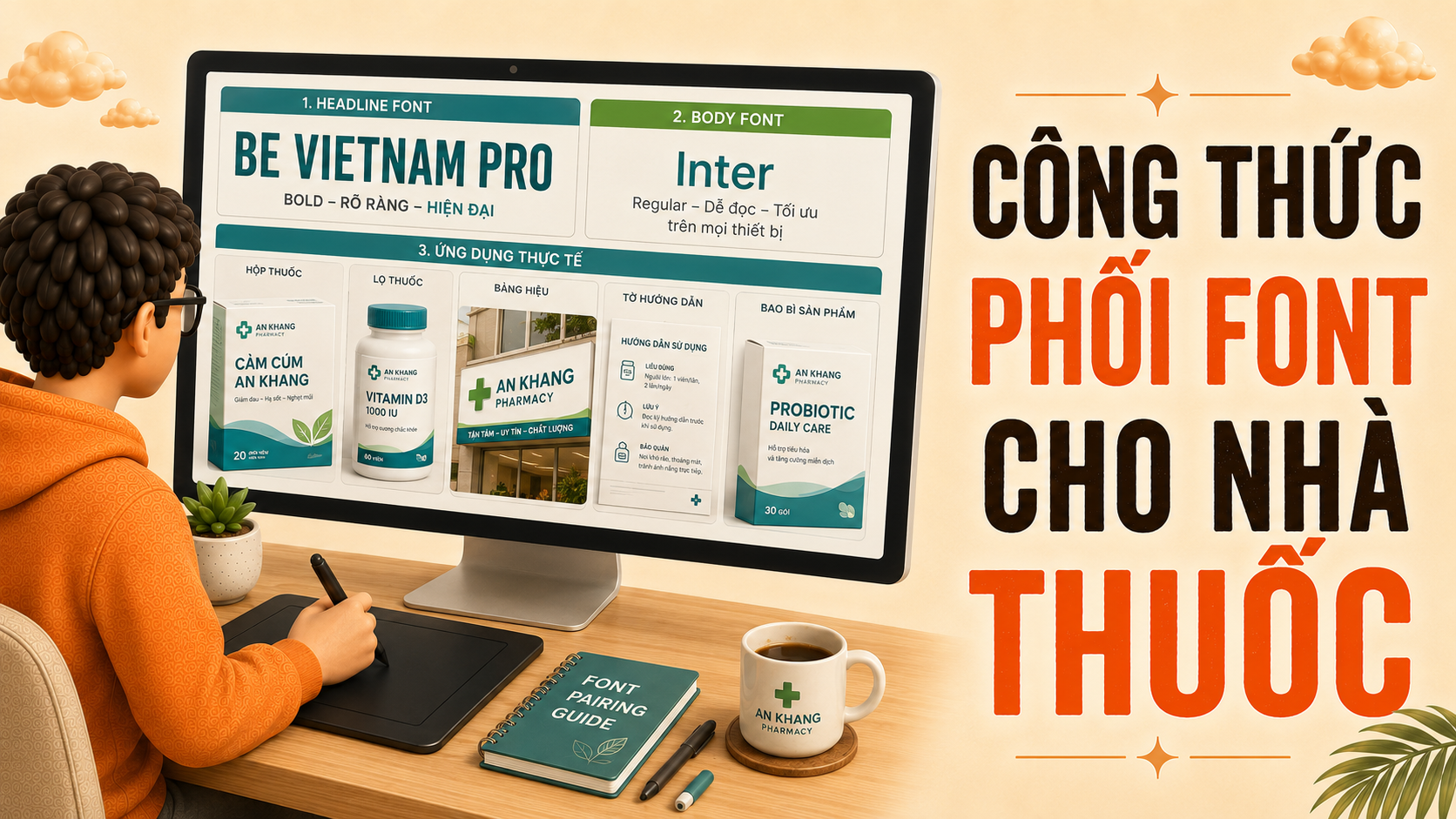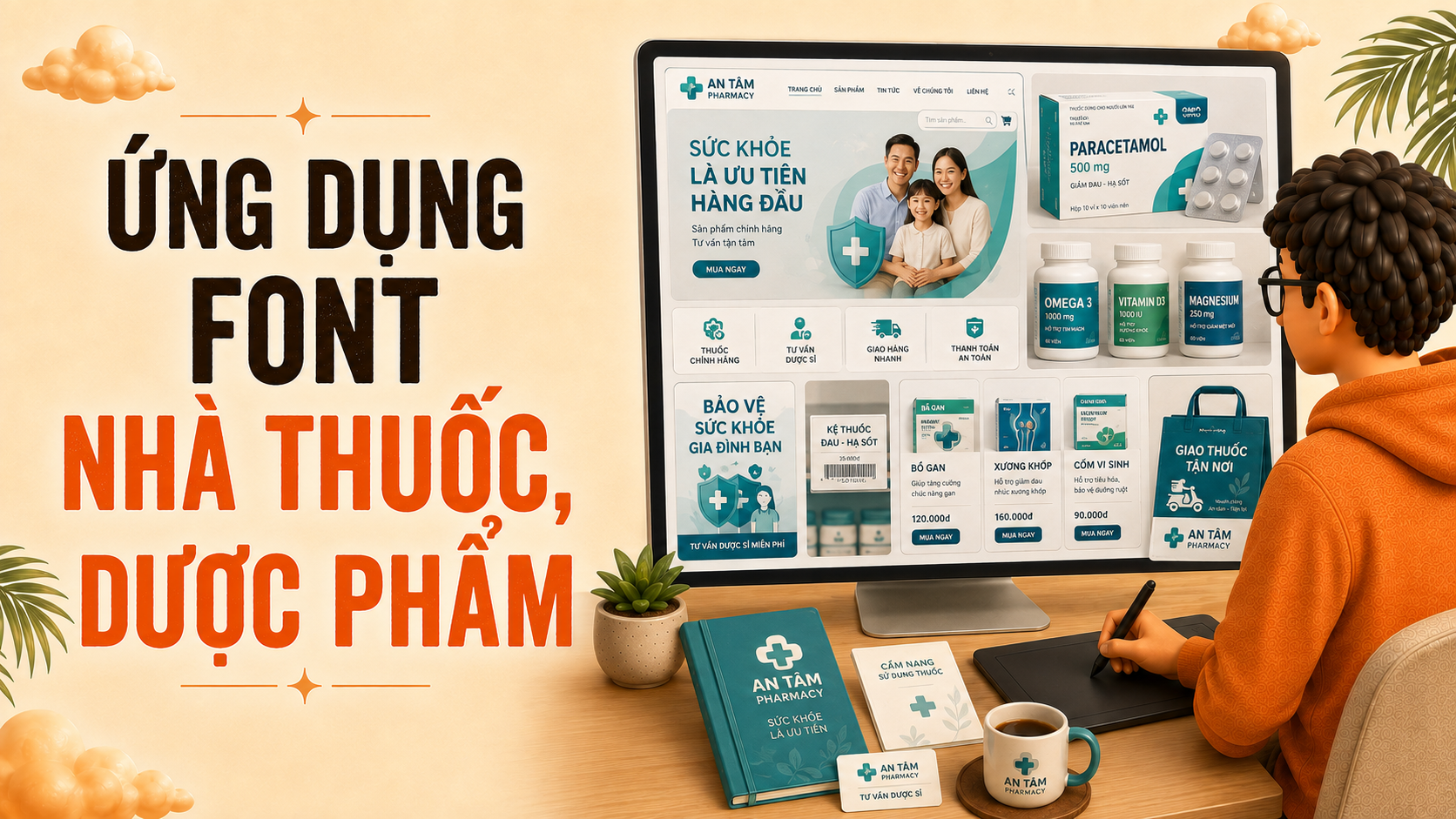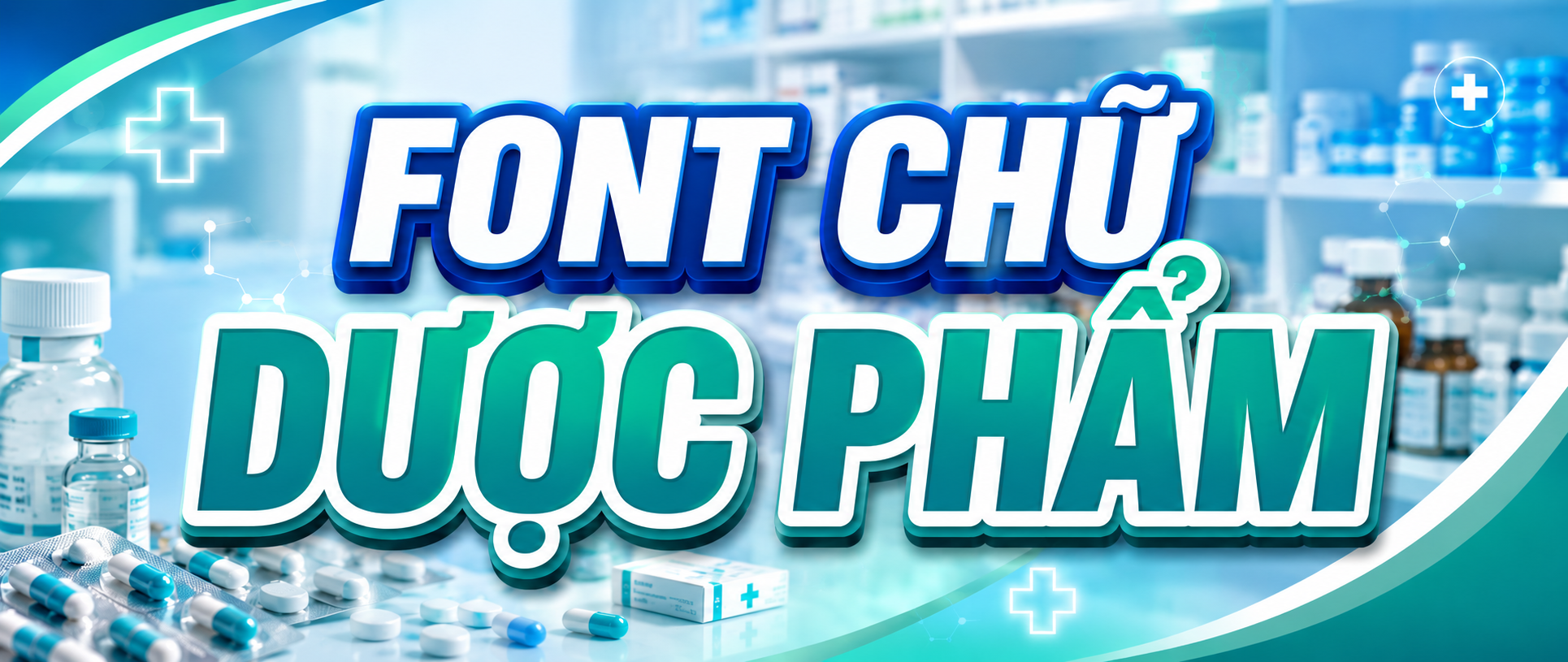
Font chữ nhà thuốc, dược phẩm không thể chọn theo cảm tính như một bài quảng cáo thông thường. Ngành dược cần sự rõ ràng, tin cậy và đúng mực vì người đọc thường đang tìm thông tin liên quan đến sức khỏe, sản phẩm chăm sóc cơ thể, thuốc, vitamin, thực phẩm chức năng hoặc hướng dẫn sử dụng. Một font đẹp nhưng khó đọc có thể làm bảng hiệu kém chuyên nghiệp, bao bì thiếu an tâm hoặc poster tư vấn bị rối.
Nhà thuốc là nơi khách hàng cần cảm giác an toàn. Họ nhìn bảng hiệu để nhận diện nhanh, nhìn poster để hiểu chương trình tư vấn, nhìn bao bì để phân biệt sản phẩm và nhìn nhãn phụ để đọc thông tin quan trọng. Vì vậy, font chữ trong ngành này phải ưu tiên độ đọc, sự sạch sẽ và tính ổn định.
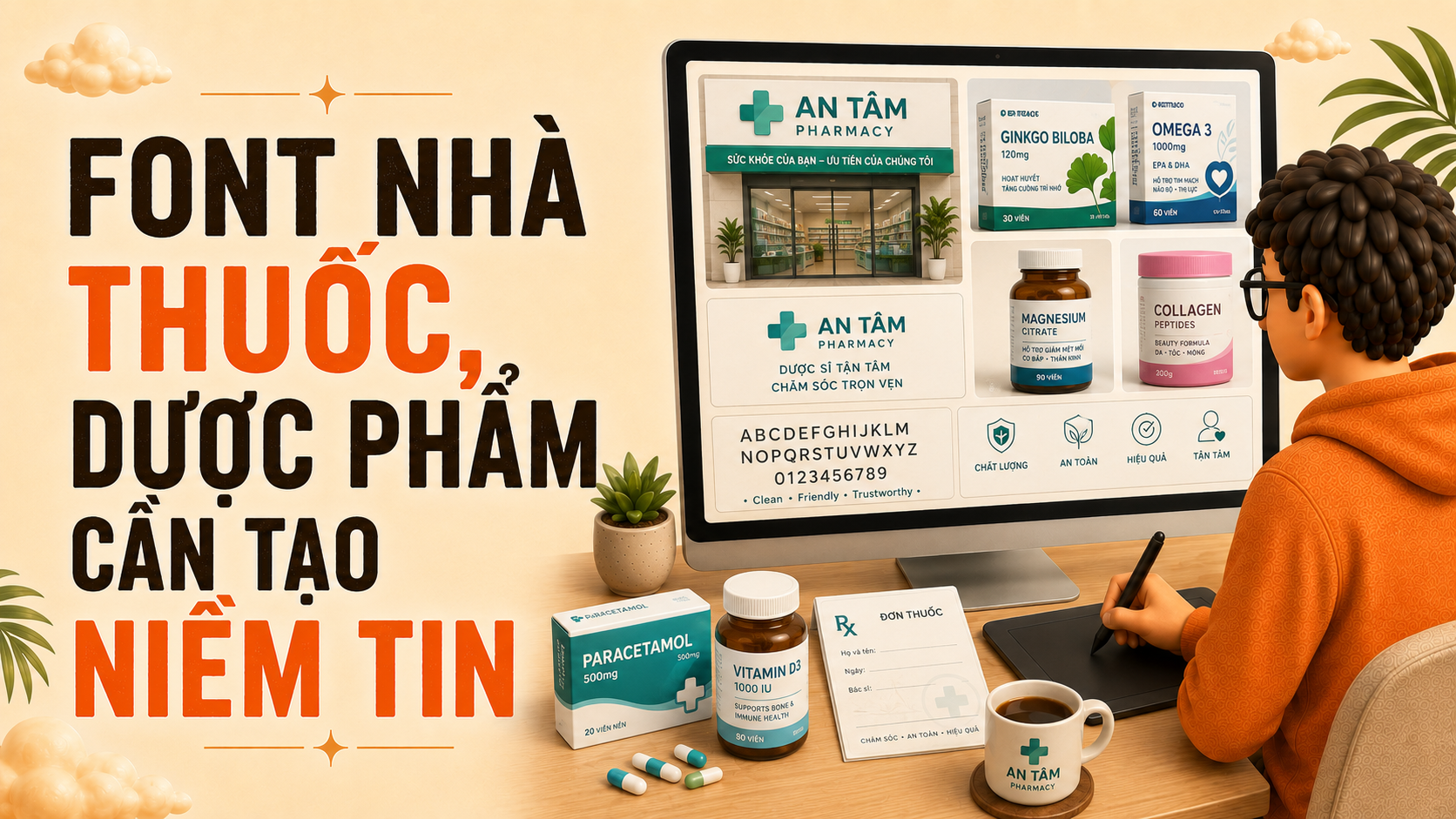
Một font quá bay bổng sẽ không hợp cho tên thuốc, hướng dẫn dùng hoặc bảng giá. Một font quá nặng có thể làm poster khuyến mãi giống bán lẻ đại trà, thiếu cảm giác chuyên môn. Một font quá mảnh lại dễ mất nét khi in trên tem nhỏ, hộp giấy, nhãn chai hoặc banner điện thoại. Điểm cân bằng tốt nhất là chọn font rõ, có dấu tiếng Việt đẹp, nét chữ hiện đại và không gây hiểu nhầm.
Với nhà thuốc, chữ không chỉ để trang trí. Chữ là một phần của trải nghiệm mua hàng. Khi font trên bảng hiệu, túi giấy, tem giá, poster kệ thuốc và fanpage thống nhất, thương hiệu nhìn chuyên nghiệp hơn và dễ được ghi nhớ hơn.
Bao bì thuốc, tem phụ, nhãn chai, nhãn hộp và tag sản phẩm thường có nhiều chữ nhỏ. Font cần có khoảng cách chữ thoáng, số dễ đọc và dấu tiếng Việt không bị chồng. Nếu thiết kế có nhiều dòng như công dụng, thành phần, cách dùng, đối tượng sử dụng, bảo quản, font sans-serif sạch luôn là lựa chọn an toàn.
Nhà thuốc cần đáng tin, nhưng không nên quá xa cách. Logo và bảng hiệu có thể dùng font hiện đại, gọn và thân thiện. Poster tư vấn gia đình, vitamin, mẹ và bé có thể mềm hơn một chút. Dược mỹ phẩm và sản phẩm chăm sóc sức khỏe cao cấp có thể dùng font thanh lịch hơn để tăng cảm giác chất lượng.
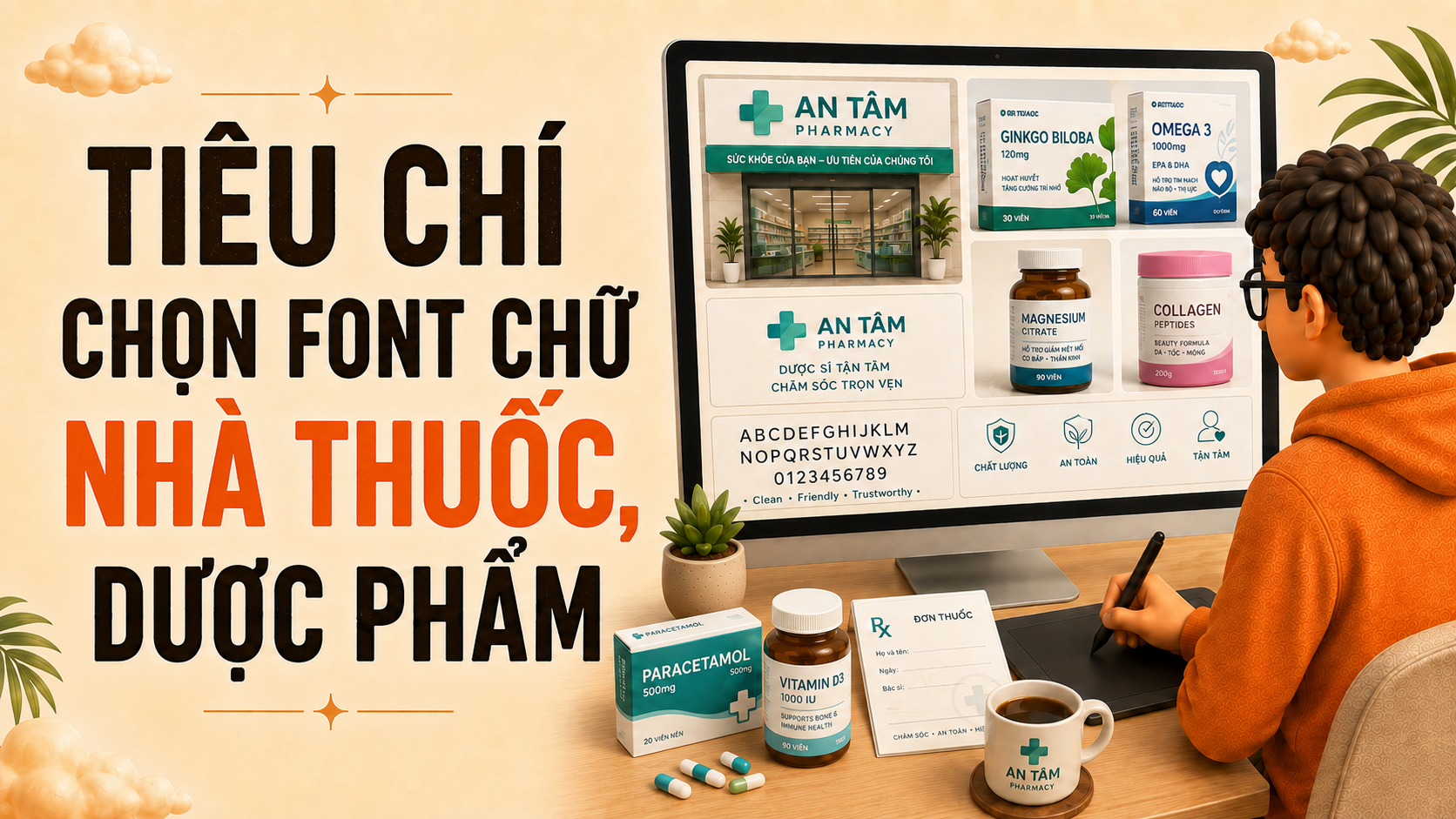
Các cụm như nhà thuốc, dược phẩm, sức khỏe, bổ sung vitamin, hỗ trợ tiêu hóa, chăm sóc da, tăng đề kháng, phòng ngừa, hướng dẫn sử dụng đều có nhiều dấu. Font Việt hóa tốt giúp dấu cân, chữ không lỗi và thiết kế giữ được sự chuyên nghiệp khi triển khai nhiều nội dung.
Một bộ font hiệu quả nên dùng ổn trên bảng hiệu, poster, bao bì, website, app, sàn thương mại điện tử, ảnh social và tài liệu tư vấn. Nếu chỉ đẹp trên một banner lớn nhưng đọc kém trên nhãn hộp, font đó không nên làm font chính.
Sans-serif là nhóm font quan trọng nhất với nhà thuốc và dược phẩm. Nhóm này hợp với logo nhà thuốc, bảng hiệu mặt tiền, biển chỉ dẫn quầy, poster tư vấn, bảng giá dịch vụ, website bán hàng, app đặt thuốc và nội dung chăm sóc khách hàng. Ưu điểm lớn nhất là dễ đọc, sạch và tạo cảm giác hiện đại.
Nếu làm logo nhà thuốc, hãy ưu tiên font có nét vừa phải, không quá mảnh và không quá góc cạnh. Nếu làm bảng hiệu, cần kiểm tra chữ ở khoảng cách xa, đặc biệt với các cụm như Nhà thuốc, Pharmacy, Dược phẩm, Chăm sóc sức khỏe, Tư vấn dược sĩ. Với poster tư vấn, font nên đủ rõ để người xem lướt nhanh vẫn nhận ra thông điệp chính.
Công thức dễ dùng là chọn một sans-serif làm font chính cho toàn bộ hệ thống. Dùng cùng font đó cho tiêu đề, mô tả, CTA, giá và hotline bằng cách thay đổi weight, kích thước, màu sắc. Cách này giúp thương hiệu nhà thuốc nhìn thống nhất, gọn và đáng tin hơn.
Bao bì dược phẩm cần vừa bán hàng vừa giữ tính nghiêm túc. Hộp thuốc, hộp vitamin, nhãn siro, nhãn viên uống, sản phẩm chăm sóc sức khỏe, sản phẩm hỗ trợ miễn dịch hoặc tiêu hóa đều cần font rõ ở nhiều cấp thông tin. Tên sản phẩm có thể nổi bật, nhưng phần mô tả công dụng, quy cách, thành phần và cảnh báo phải dễ đọc.
Với thực phẩm chức năng cao cấp, có thể dùng luxury sans-serif hoặc serif hiện đại cho tên dòng sản phẩm. Nhưng phần thông tin cần đọc kỹ vẫn nên dùng sans-serif sạch. Đừng để toàn bộ bao bì dùng font quá mảnh, vì khi in trên hộp nhỏ hoặc nhãn chai, chữ có thể bị chìm.
Một layout bao bì dễ kiểm soát thường có ba lớp chữ: tên sản phẩm lớn, mô tả lợi ích ngắn và thông tin kỹ thuật nhỏ. Mỗi lớp nên có vai trò rõ. Nếu font tên sản phẩm đã có cá tính, font mô tả và thông tin phụ nên tiết chế để không làm bao bì bị ồn.
Font chữ nhà thuốc, dược phẩm tốt phải rõ, sạch, đáng tin và dùng ổn trong nhiều bối cảnh: logo, bảng hiệu, bao bì, nhãn sản phẩm, poster tư vấn, website và social bán hàng. Hãy bắt đầu bằng một sans-serif Việt hóa làm font chính, sau đó bổ sung font nhấn nếu cần cao cấp, thân thiện hoặc mạnh hơn cho chiến dịch.